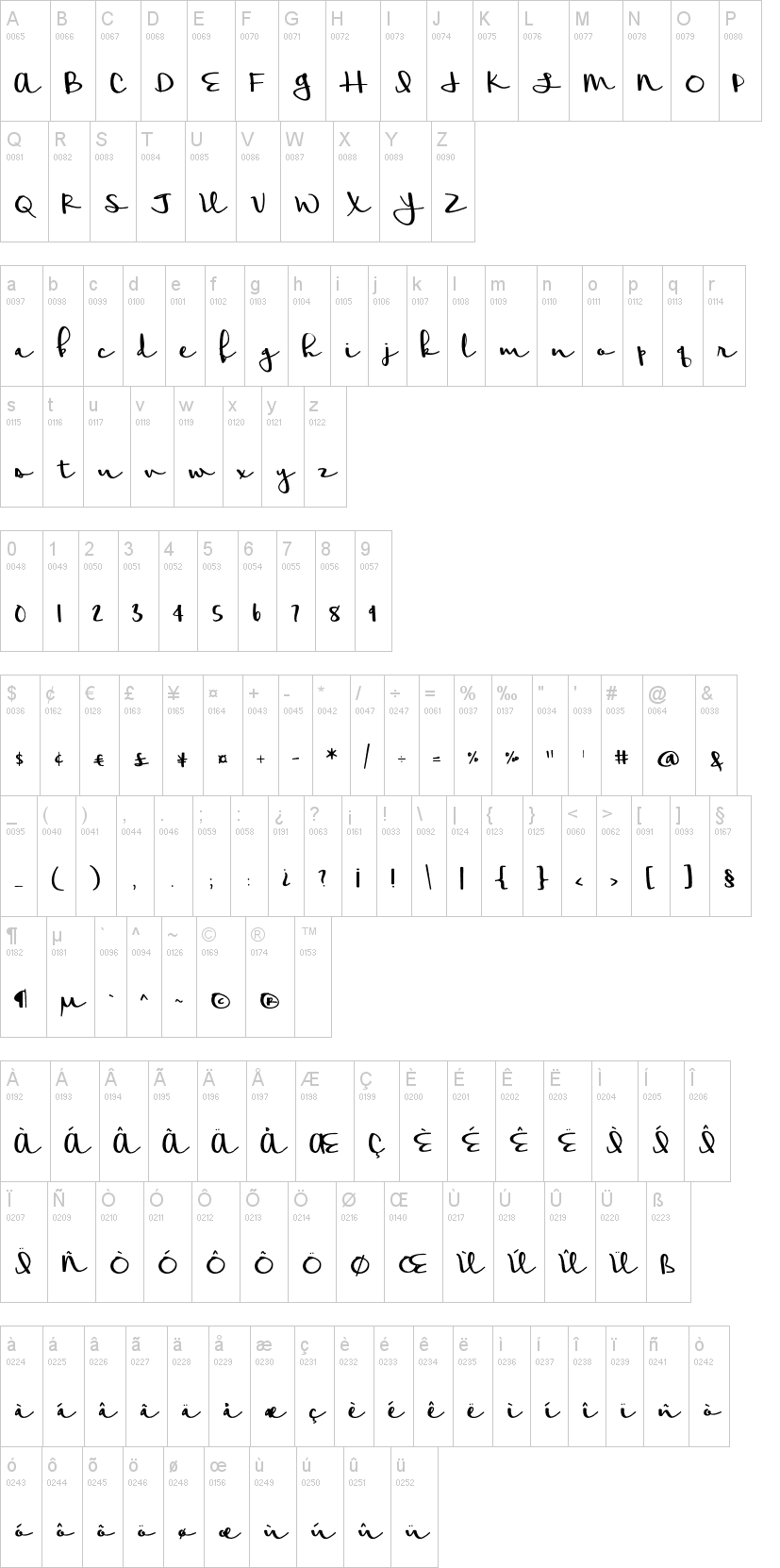
Meadowbrook字体是一款由Samuel O. White发明的楷体字体,它受到了西洋文字系统的影响,具有精致的折线,优美的比例,以及简洁的外观。Meadowbrook字体的字体结构使其具有高度的可读性和清晰的外观,使其适合用于报纸,杂志,书籍,海报,标志,标签等。Meadowbrook字体可以用于网页设计,因为它的字体文件可以被轻松地转换为网页字体。内容介绍
Meadowbrook是一款非常不错的手写艺术字体,具有很好的视觉感,适合于文化类的宣传设计、商业类品牌的广告和产品包装设计以及个性化文字排版等较多场景。